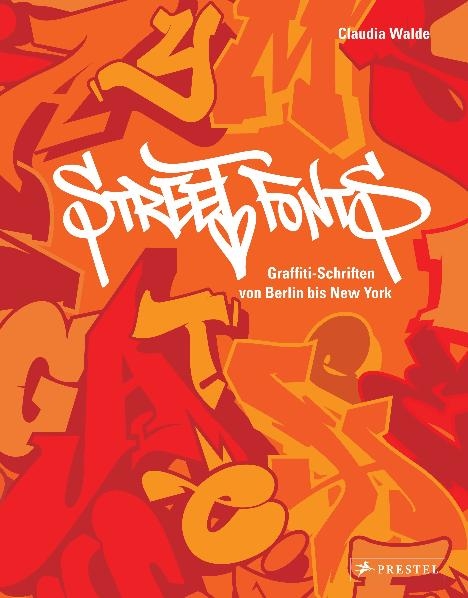
Street Fonts
Graffiti-Schriften von Berlin bis New York
Das ABC der Graffiti-Kunst
Die Schriften der Graffiti-Writer inspirieren Designer und Grafiker seit vielen Jahren. Doch noch nie wurden sie systematisch als vollständige Alphabete zusammengestellt. Über 150 Graffiti-Künstler aus der ganzen Welt, darunter viele deutsche Graffiti-Writer, haben speziell für dieses Buch Alphabete entworfen. Schwarz-Weiß-Skizzen, Skulpturen, digitale Illustrationen, Installationen und andere Ausdrucksformen sind entstanden. Die Ergebnisse repräsentieren nicht nur die internationale Street Art-Szene, sondern geben gleichzeitig einen Einblick in den faszinierenden Kreativprozess.